今月注目の無料でダウンロードできる英語フォントを紹介します。
Butler Free Font
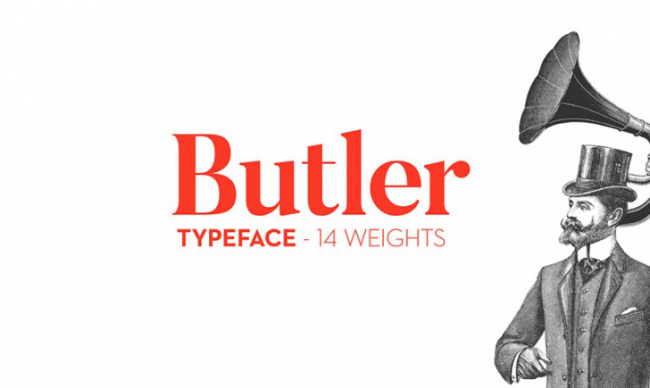
14種類のウェイトがセットになった英字フォントです。
Star Full Inline Font
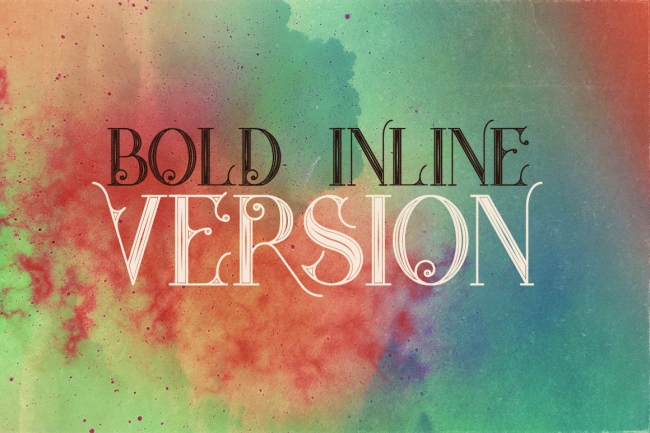
太字に細いラインが加わった、おしゃれなインラインフォントです。
Shelby Inline Font
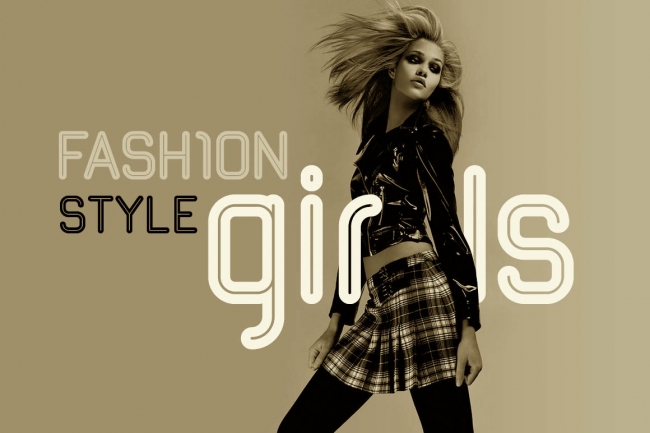
先端が丸まったデザインが特徴的なインラインフォントです。
Black Mask Typeface
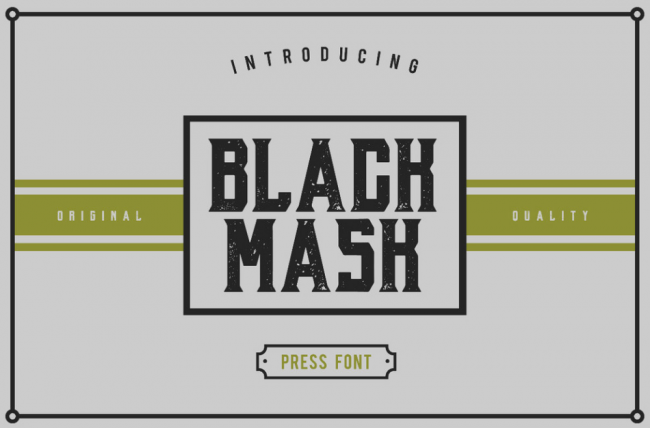
ヴィンテージな印象のフォントです。
Bernier Font
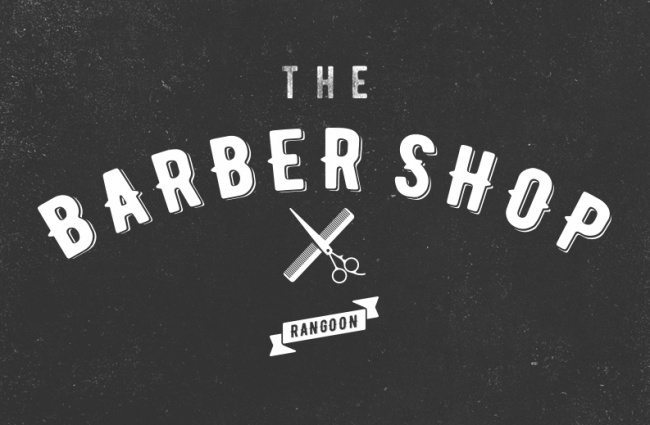
3種類のスタイルがセットになった、ロゴや見出しデザインに使えるおしゃれなデザインのフォントです。
Phenomena
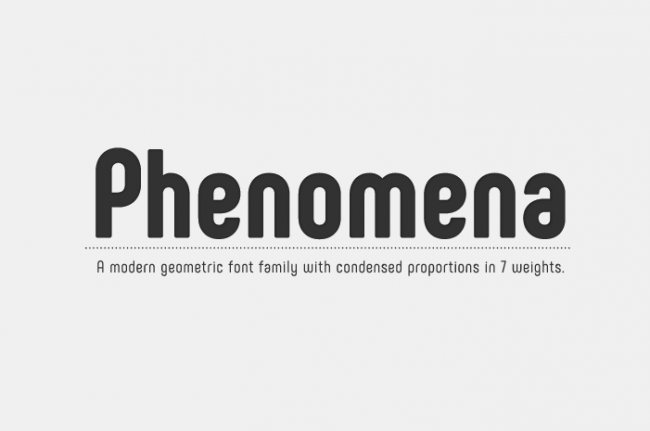
モダンなデザインで、少しだけレトロな感じのするサンセリフのフォントです。
Bravery
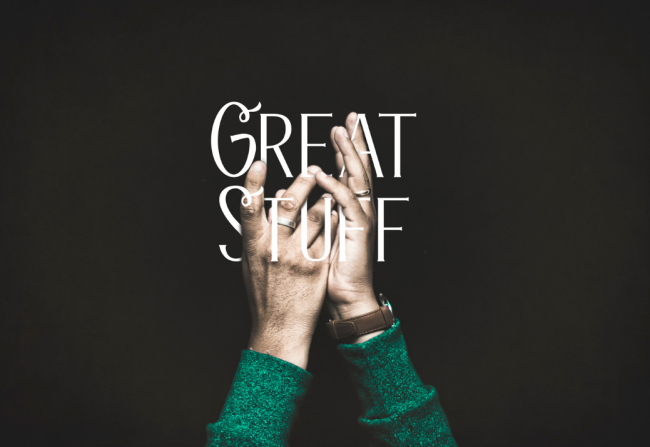
楽しくてエレガントなフォントです。
AQUA
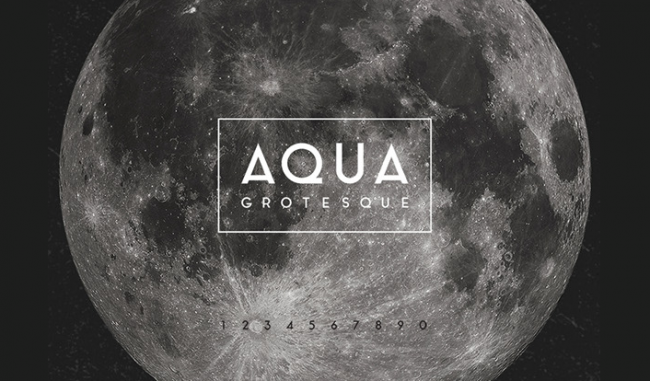
1940年代にインスピレーションを受けた、レトロなビンテージフォントです。
Arkana
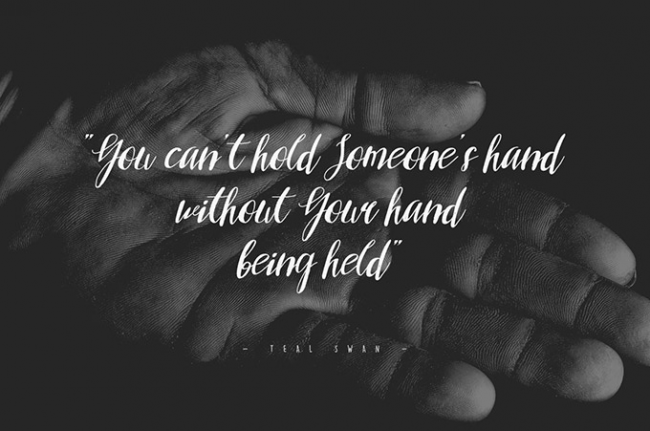
筆記体風の英字フォントです。深みのあるデザインです。
Sitka Brush
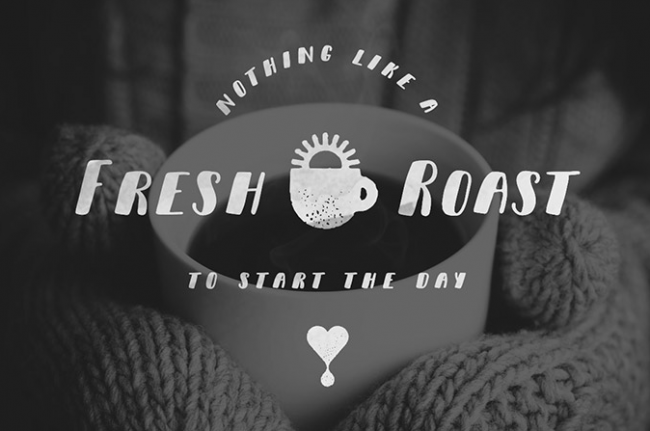
デザインに使いやすい、かわいらしい丸みとほどよい斜体が特徴のフォントです。
Sequel
YoungSerif
読みやすい、セリフ体のフォントです。
Elianto
未来的なデザインの英字フォントです。
PLENTO
クリエイティブなラインスタイルのフォントです。
NEW YORK
ポスターや見出しに使える英字フォントです。
FREE Homizio Nova Font
レギュラー、ライトとそれぞれのイタリックがセットになった、サンセリフフォントです。
Haze Typeface
インパクトのあるデザインのブラシフォントです。
The FREE South Rose font
いかり型の装飾が特徴的なオリジナリティのあるフォントです。
WADON Font Free
デザインのアクセントになる、太古の文字のような印象のフォントです。
Asteroid Font – FREE FONT